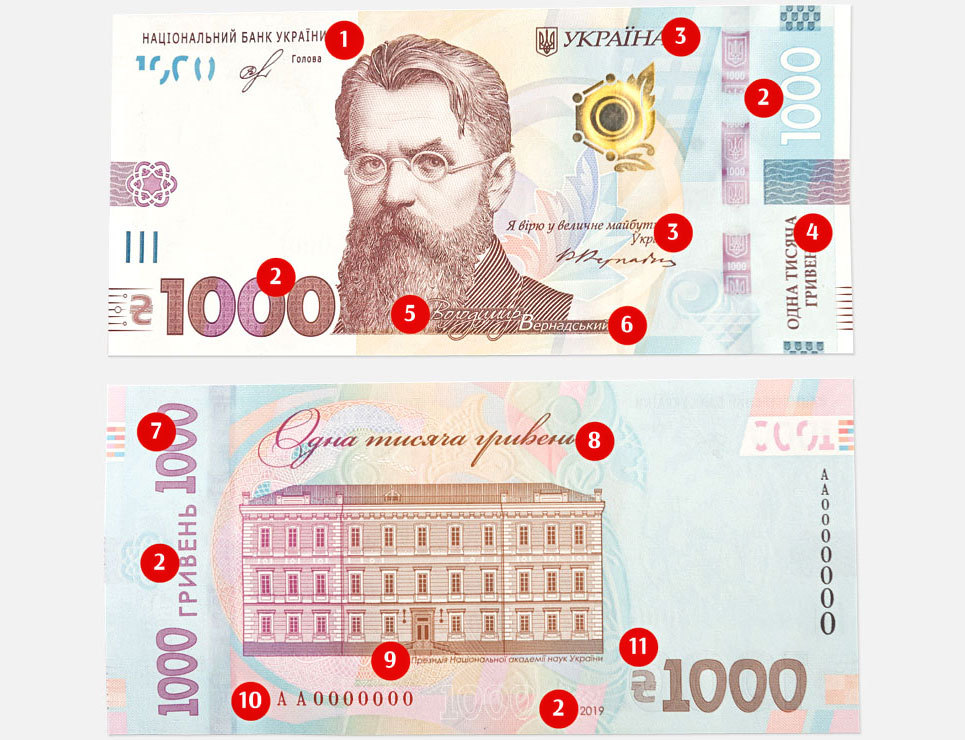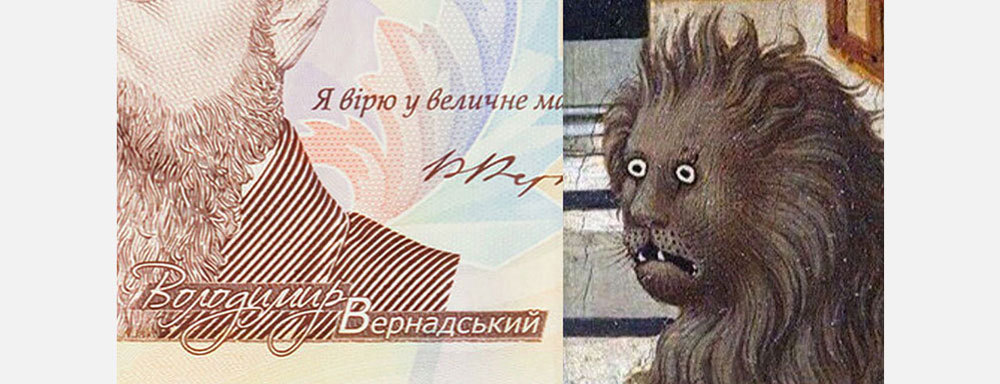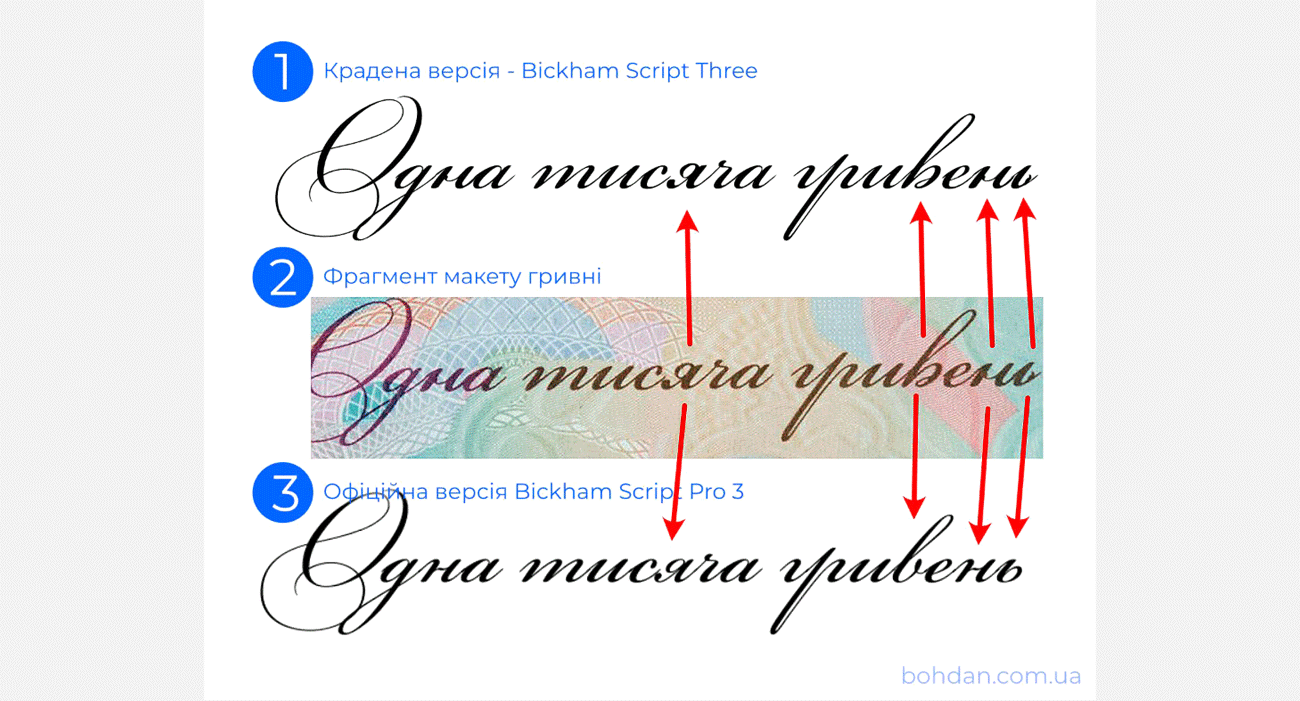
Як зробити 1000 гривень без піратських шрифтів
На цю тему мене підштовхнув скандал з піратським шрифтом на новій банкноті 1000 гривень, зображення якої Національний Банк України на початку липня 2019 року.
Нелегальну й неякісну кирилічну версію шрифту Bickham Script від Adobe на банкноті спочатку впізнали українські дизайнери. Їх зауваження інтернет-видання Telegraf.Design, а шрифтар Богдан Гдаль автору оригінального шрифту Франку Грісхамеру, який також впізнав на банкноті кирилічну адаптацію російської дизайнерки Олександри Гофман, зроблену з порушенням ліцензії Adobe.
, на жаль, була суперечливою. Добре, що вони принаймні не намагались назвати цей «шрифтовий букет» додатковим ступенем захисту.
Дизайн сучасних гривень – не те, чим можуть пишатися українські дизайнери. Навіть перші гривні 1992 року випуску мали якісніший дизайн. Різних шрифтів було менше ніж сьогодні, вони були унікальними й мали спільну стилістику з орнаментами та ілюстраціями.
Дизайн грошей дуже багато говорить про країну, це візитівка держави, міні екскурсія, яка розповість про її минуле, сьогодення та майбутнє, про те, чим пишаються люди і як вони це презентують. Один піратський шрифт не говорить, що українці є піратами. Набагато страшніші 11 різних шрифтів в одному дизайні.
Будь-які написи, зроблені різними шрифтами, різного розміру й кольору, очевидно, мають читатися по-різному. Також вони сприймаються по черзі, залежно від їх розміру, контрастності та інших якостей. Кожна риса напису пов’язана зі змістом тексту.
Типографія, як частина композиції є візуальною мовою. Вибір шрифтів та інших якостей написів створює драматургію. Написи – це актори, які виходять на сцену в різних костюмах і різними голосами розповідають історію. Її свідомо зчитують професіонали, а прості глядачі сприймають підсвідомо.
Візьмемо, наприклад, аверс нової 1000 гривень. Кожен напис зроблено в своєму стилі, навіть в імені Володимира Вернадського використано 2 шрифти + буквиця, і все це з контуром і на окремих плашках. В чому мета? Що можна розповісти про Україну за допомогою вісьмох різних шрифтів?
З професійної точки зору таке рішення можна трактувати або як іронічний карнавальний безлад, або як провінційне прагнення зробити «по-багатому». Ця імітація вишуканості схожа на роботу професіоналу не більше, ніж середньовічні зображення левів схожі на реальних левів.
Дилетантську типографію на грошах можна було б пробачити країні, де немає власних дизайнерів і ніхто не розуміється на шрифтах. Але Україна має дизайнерів, яких визнають у всьому світі, і завжди їх мала. У нас є власні традиції каліграфії та друкарства, десятки шрифтарів, які зробили сотні сучасних цифрових шрифтів!
Яким має бути дизайн гривні
До будь-якого символу держави є очевидні загальні вимоги. Дизайн гривні має бути:
- якісним і професійним;
- чистим з правової точки зору;
- базуватися на українській інтелектуальній власності;
- відображати цінності України.
Відображення цінностей – єдиний пункт, який є складним. Україна, як і інші країни, має безліч цінностей, якими можна пишатися, але ми не можемо на невеличкій купюрі передати їх усі. Розробник дизайну банкнот має обрати найголовніші позитивні символи країни і зробити акцент на них, як у туристичних брендах, тільки трохи складніше.
У бренді 2013 року Україна пропонувала гостям магнетизм наших природних краєвидів, цікаву традиційну культуру, яскраві враження. А у 2018 році наша країна наголошувала на своїй перспективності. Не віночки зі стрічками, а осередок модернізму і прогресу. Будь-яка з цих або інших українських цінностей може бути основою ідеї дизайну гривні.
Унікальні літери чи готові шрифти?
Цей вибір залежить від обраних цінностей. Якщо ми понад усе цінуємо нашу історію, унікальні традиції, то логічно показати світові максимум автентичного, українського. Графіка, орнаменти, написи мають здаватися безцінним скарбом, який плекала уся нація, охороняючи від ворогів тисячу років. Звичайно, такий дизайн передбачає унікальну літерацію чи навіть каліграфію в єдиному стилі з усіма іншими елементами.
Такий підхід ми бачимо в дизайні перших гривень 1992 року. Тут усі елементи зроблені в традиційному стилі українськими художниками Василем Лопатою (ілюстрації) та Борисом Максимовим (дизайн, шрифти).
Яскравий приклад протилежного підходу – акценту на сучасності – можна побачити в новому дизайні норвезьких грошей. До речі, їх нову купюру 1000 крон планують ввести в обіг одночасно з нашою тисячею гривень, у жовтні 2019. Цей дизайн дає три дзвінкі ляпаси прихильникам демонстративного споживання усіляких розкішних пишнот. По-перше, використали лише одну готову шрифтову гарнітуру – . По-друге, шрифт зробив швейцарець Адріан Фрутігер. І по-третє, де ж ваші герої? Жодного короля вікінгів!
І все ж таки, це стримане мінімалістичне рішення не виглядає примітивним чи непрофесійним. Дизайн крон розповідає історію про море та усе, що воно споконвіку приносить норвежцям. Цінності, які вони передають, я б назвав гуманістичний еко-френдлі модернізм. Цей дизайн зацікавив багатьох людей по всьому світу. Національний Банк Норвегії навіть зняв , що розкриває історію створення нових банкнот. Цікава деталь – аверс та реверс купюри робили різні дизайн-студії!
Замовляти ексклюзивні шрифти це звична практика у розвинутих країнах. Дуже приємно, що це стає нормальним і для України. У нас вистачає людей, які можуть зробити унікальні шрифти, каліграфію або літерацію для українських банкнот і монет. Пропоную шортліст українських майстрів шрифту і каліграфії, які мають нагороди та медійність: , , , , , .